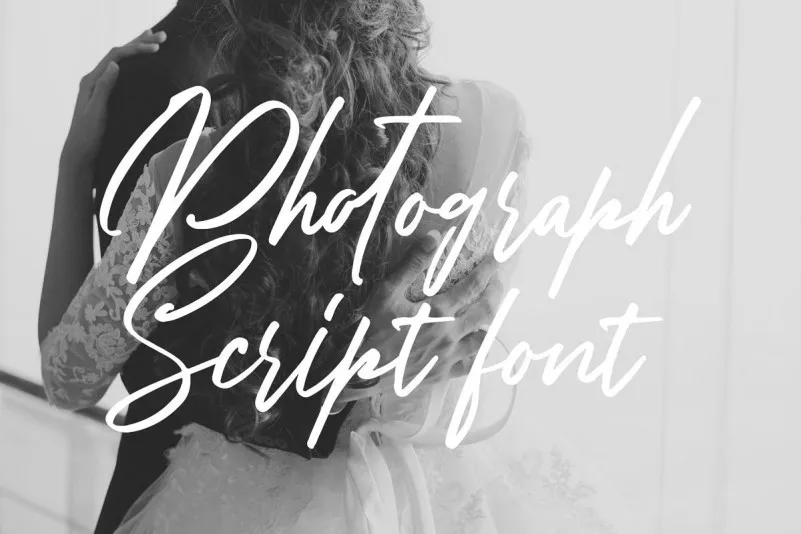
Bellarinde Script Font
Introduzimos a Bellarinde Font. Esta é uma nova fonte script escrita à mão que irá revolucionar a forma como você apresenta texto. Essa elegante fonte pode tornar qualquer mensagem luminosa, luxuosa e moderna ao mesmo tempo. Ela foi projetada e compartilhada pela Hanzel Studio e cada letra foi cuidadosamente moldada para que seu texto fique encantador e único. Com um estilo de fonte script contemporâneo, esta font é ideal para uma ampla gama de projetos: fotografia, marca d’agua, citações, design web, cabeçalho da blogueira, cartazes, casamento, marca, logo, moda, vestuário, letra e convites. Seja você criando seu próprio selo de marca ou desenvolvendo um site de moda inovador, a Bellarinde Font certamente se encaixa perfeitamente em suas necessidades.